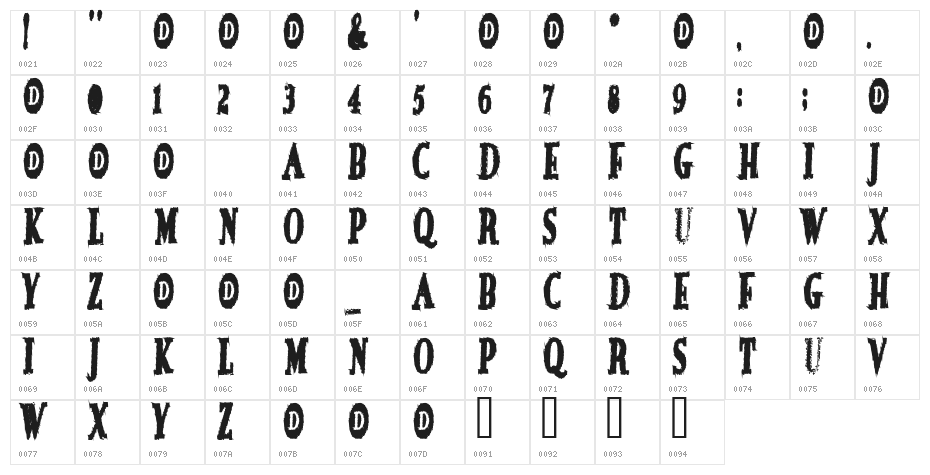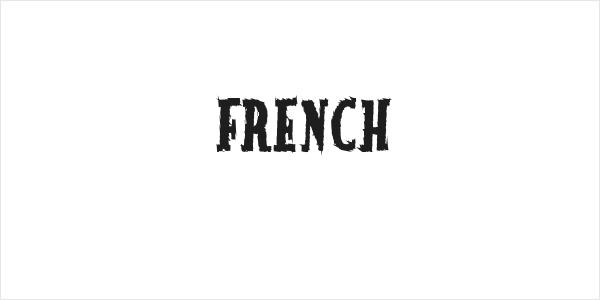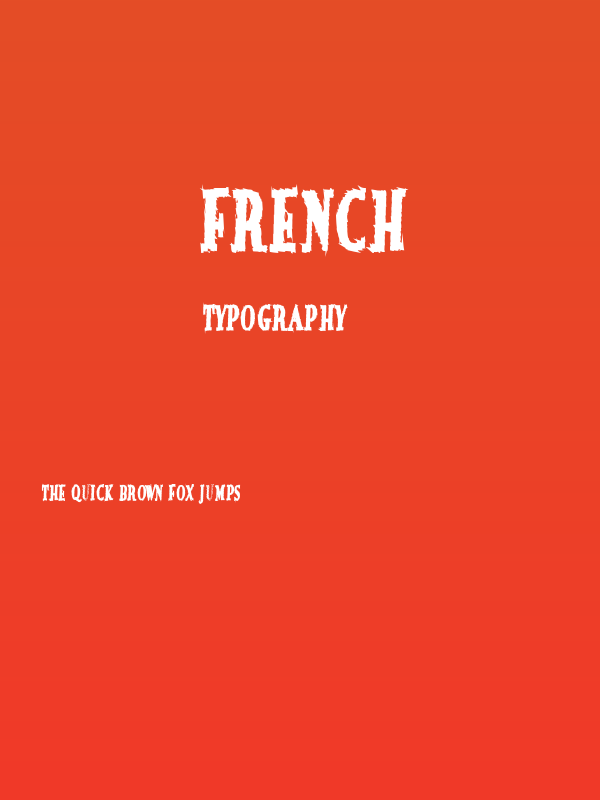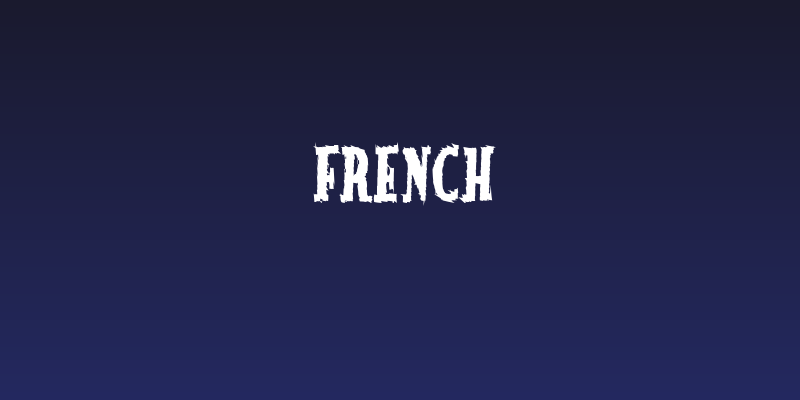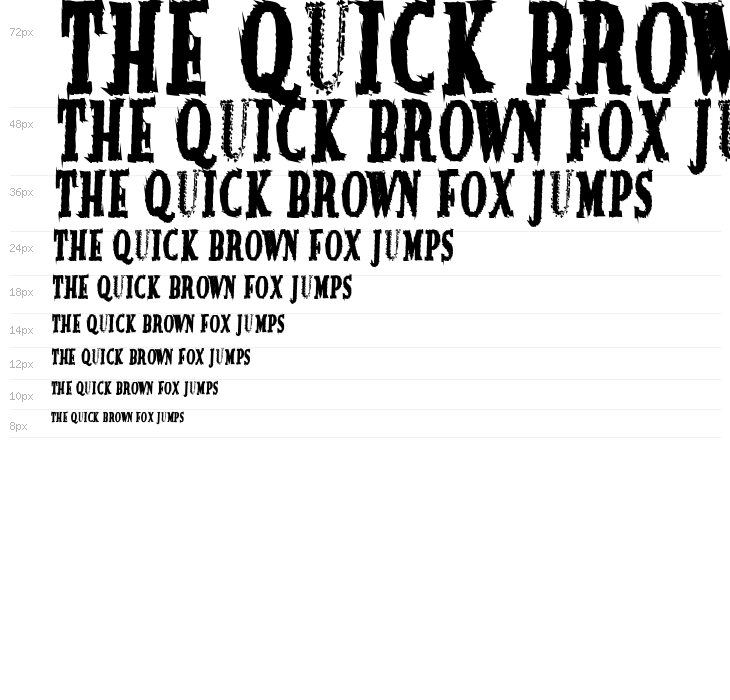
French Font
| Categorías | Messy |
| Estilo general | Vintage, Decorative |
| Proyectos propuestos | Ideal for poster designs, album covers, branding for edgy or vintage-themed products, and any project needing a bold statement. |